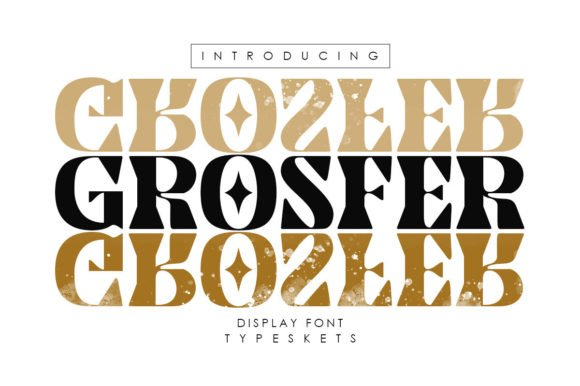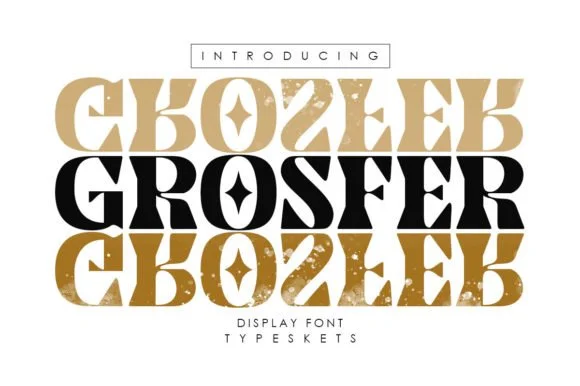
Название: Grosfer Font (2021)
Grosfer - это крутой, смелый и толстый шрифт.
Этот шрифт читается как сильный, уверенный и динамичный и может добавить свирепый характер в ваши проекты.